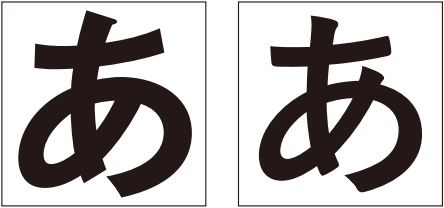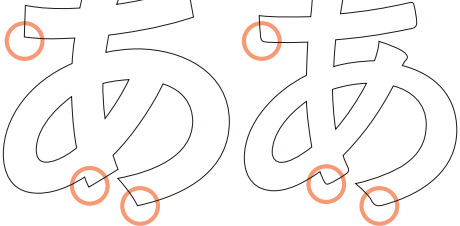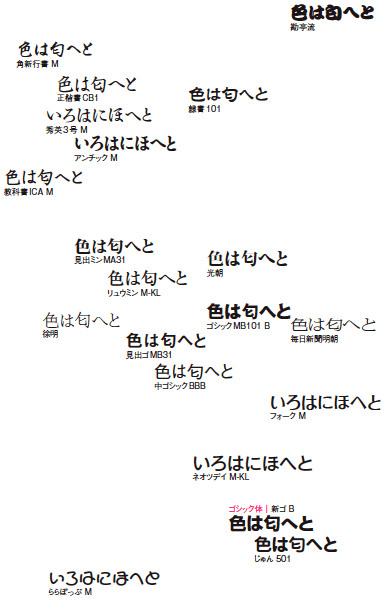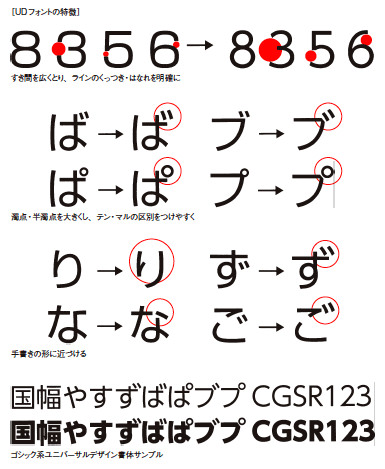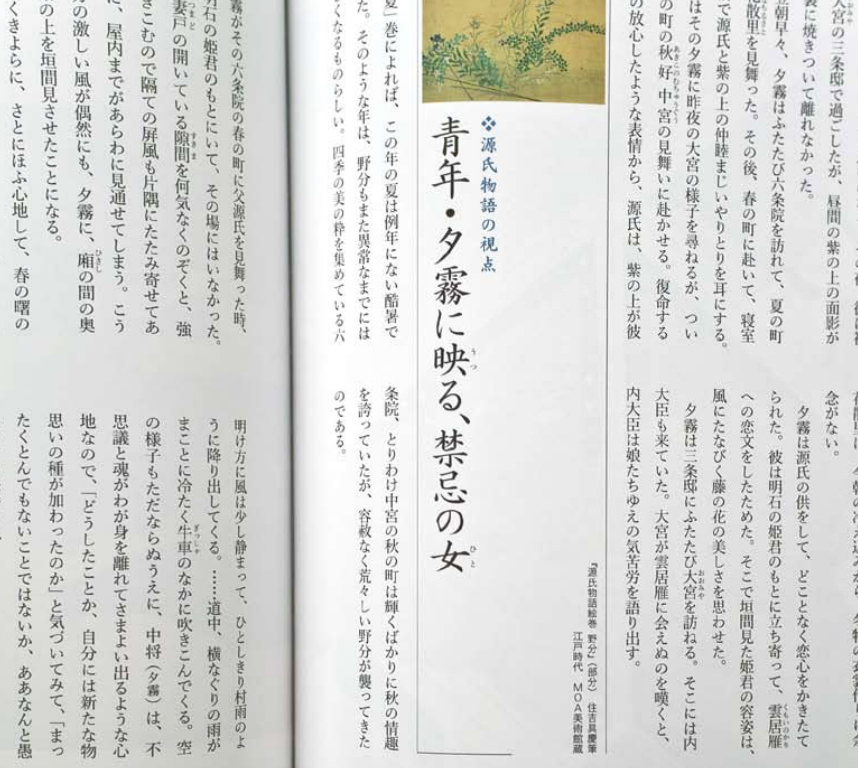
第九回 書 体 を 選 ぶ 2 和 文 書 体 を 見 分 け る
さて、前章では欧文書体の分類についてひととおり書いてみましたが、残念ながら、和文書体は未だに体系的に分類されるに至ってはいません。しかし、いくつかの試みを見ることはできます。なかでも、七章で紹介した、小宮山博史氏の「日本語書体の分類」(『基本日本語活字見本集成』収録)は、ひとつの基準になるものでしょう。それを承知の上で、ここでは、欧文書体に倣って、時代・かたち・用途で分類することを試みてみたいと思います。
時代に
よる分類
まず時代の分類を考えると、近代活字期、写真植字期、デジタル書体期の三期に分けることができます。
近代活字は、まだ和様が残る崩れた魅力の味わえる書体群を前期、築地体や秀英体といったおなじみの明朝体がかたちを成してくる後期の、二期に分けるのがいいでしょう。
近代活字の中心となる築地体は、改刻を重ね、多くのフォロワーを育てました。
それは、現代のかな書体や復刻書体にまで連なっています。おもな改刻書体として、写植期の石井明朝体(写研)、デジタル書体のリュウミンオールドかな(モリサワ)、游明朝体5号かな、36ポかな(字游工房)、復刻書体として、築地体初号仮名、後期五号仮名(大日本スクリーン)などを挙げることができます。秀英体も築地体を下敷きにして生まれた書体ですが、独自の発展を遂げて、今では、活字・写植・デジタル書体、三世代にまたがって開発が続けられている唯一の書体となりました。
築地体と秀英体は明朝体の二大源流といわれています。それぞれに特徴がありますから、これらを見分けるのはさほど難しくはないでしょう。同様の書風を持つゴシック体も近代活字期の書体に分類することができます。
写植期は、タイプフェイスデザインの開花期でもあり、さまざまな書体が登場します。なかでもフトコロが広くボディいっぱいに設計された書体がこの時期の特徴でしょう。仮名が大きくなるのもこのころです。ファミリー化され、見出しと本文が同じかたちになったことも特徴にあげていいでしょう。代表的な書体として、ナール、ゴナ、本蘭明朝(写研)、新ゴ、ツデイ(モリサワ)などを挙げることができます。デジタル書体ではありますが、ヒラギノ(大日本スクリーン)もこのグループの特徴を備えています。
デジタル書体は写植資産の電子化がようやく一段落したところですが、デジタル書体ならではの特徴も見えはじめています。たとえば、CTPなど印刷技術のデジタル化によってデータが精細に再現されるようになると、逆にシャープなエッジが嫌われるようになり、起筆部、終筆部だけでなく"はね"や"はらい"の先端も丸く処理されるようになりました。そういうエッジの丸めが特徴のひとつとなっています。
また、改刻書体の流行とも関連していると思われますが、写植書体とは逆に、小振りの文字が歓迎されるようになります。フトコロは絞られ、筆の運びを再現するようなかたちが好まれるようになってきました。そういった活字がえりが見受けられるなか、印刷・スクリーン表示兼用のアウトラインフォントやUDフォントへの取り組みにデジタル書体独自の発展を見ることができます。
三つの時代の特徴から分類すると、大きく、築地体、秀英体に代表される「オールドスタイル」、小塚明朝、新ゴといった「モダンスタイル」に分かれ、その中間の特徴を持つ、ヒラギノ明朝、ゴシックMB101といった「ミディアムスタイル」とでも呼べる三つに分けられるように思います。時代順と様式の変化が一致しないので欧文のように「トランジッショナル(過渡期の)」とは呼べないのが興味深いところです。
上段:築地体のフォロワー書体(改刻、復刻含む)。
左から石井中明朝体、リュウミン・オールドかな、游築五号仮名築地体後期五号仮名、游築36ポ仮名、築地体初号かな
下段:秀英体の改刻書体
左から秀英3号、秀英5号、秀英明朝体
左:MB101 DB 右:游ゴシック B
写植書体とデジタル書体の比較。デジタル書体としてつくられた游ゴシックの方が小振り
:MB101 DB 右:游ゴシック B
尖った角と丸められた角
時代による分類
かたちに
よる分類
欧文の場合はセリフによってかたちを規定していましたが、和文にはそういうこだわりのエレメントはありません。明朝体のウロコにも規範となるような強さは見受けられません。あえて何か基準を探すなら「筆づかい」だろうと考えています。運筆や筆勢がしっかり残っているかどうか、または、それをどの程度(どのように)抽象化しているのか、そういったことがかたちを分類する上で有効な基準になるように思います。明朝体の仮名が漢字と違う楷書のような特徴を持っているように、また、漫画書体の仮名がアンチック体であるように、筆書系の書体は思っている以上に使われています。そういった観点から今あるデジタル書体を分類してみたものが左ページのマップです。
並べてみると、筆の痕跡とかたちの相関など、これまで考えてこなかったことに改めて気づかされます。やはり分類の基準をひとつに定めることは、体系的に理解する上で重要なことなのでしょう。
[モリサワ書体におけるかたち(筆づかい)による分類マップ]
上下は筆の痕跡、左右はかたちの抽象度で分布した。左ほど手書きのかたちが残っている。距離は等歩度であることを心がけたが、うまくいっているのかどうかわからない。あくまで試案としてご勘弁いただきたい。
用途に
よる分類
UDフォントの特徴
最後に用途による分類です。和文活字は見出し用、本文用でタイプフェイスのデザインが異なります。先述の通りファミリー化によって区別がなくなったようにも思えますが、やはり、このふたつは分けて考えていいでしょう。同様に、書籍用と雑誌・パンフレット用も分けて考えることができます。
あとは、欧文と同じディスプレイ書体、デコラティブ(装飾)書体という分類。欧文と違うのは、用途別の専用書体が少ないこと。新聞書体と教科書体ぐらいでしょうか。これは、文字数の多さに起因するものと思われます。
前述のスクリーン表示兼用書体は、容量が軽いことに最大の特徴があり、そのため、文字数の制限はもとより、これまで成されてきた視覚調整すら省いている書体も見受けられます。しかし、本文程度のサイズではそれで見苦しいわけではなく、視覚調整の常識を疑った方がいいと思えるぐらいです。
UDフォントとはユニバーサルデザインのための文字のことです。バリアフリーであることを第一義とし、視力に障害や衰えがある人にも見誤りのないように、開口部をアキを広げたり、濁点、半濁点を大きくするなどの工夫が施されています。また、文字を直観的に見やすいように、手書きのかたちに近づけるようにかたちを変えてもいます。
いくつかあるUDフォントに共通の特色がどれくらいあるのか、そしてそれがどれほど有効であるのかは今後の検証を待たねばならないのですが、用途による分類のひとつに数えても問題ないでしょう。
近代活字以降の和文書体は、まだ歴史が浅いせいもあって、これまで積極的に整理・分類されることはありませんでした。文字数もさることながら、漢字、2種類の仮名、ラテンアルファベット、ローマ数字、アラビア数字と、さまざまな文字を組み合わせて使う日本語の文字表現の特性を考えると、体系的に把握することの困難さもあると思われます。逆に文字に対する自由度が損なわれるという考えもあるかも知れません。しかし、印刷書体が2000種を超え、これからオンスクリーンの表示書体と地続きになろうというところで、なんらかの書体の見分け方を手に入れなければ、書体選択もおぼつかなくなるような気がします。私は、欧文書体は「知ること」、和文書体は「考えること」で、書体選択の指標が手 にはいると考えています。
インタ
フェース
としての
書体選択
ここまで、書体選択ありきで話を進めてきましたが、ではなぜ書体を変えて文字を組まなくてはならないのでしょうか。
まず、分類の項で示したように、ある用途によってそれにふさわしい文字を選ぶということがあるでしょう。遠くから見る必要があるサイン書体は見やすいように、手元で長文を読むための文字は読みやすいように、文字の特徴を鑑みて選択します。あるいは、楽しく感じてもらうため、知的に見せたいなど、感情に訴えることも機能のうちでしょう。
機能面からだけではなく、美的な判断で書体を選ぶこともあります。太い文字の方がはっきりして見やすいことはわかっていても、もう少し細い方がきれいだ、などと言って細めの書体を選んだりします。
シニア用の読み物は大きな文字で組みます。視力の衰えへの配慮であれば、太めのゴシック体で組むのが一番読みやすいはずです。しかし、高齢者ほどゴシック体より明朝体を好むものです。理屈で考えれば、いくらウロコが付いているとはいえ、細い横画が見やすいはずもありません。しかし心理的には明朝体の方が読みやすく感じるようです。この場合、慣れや美意識が実際の機能を超えた例だと考えられます。
書体にはさらに内容を指し示す役割があります。たとえば、本文は細明朝体、見出しは太ゴシック、キャプションは中ゴシックで組むとします。そこに、脚註が加わればどうでしょう。本文と同じ細明朝でキャプションと同じ文字サイズで組まれていると、本文ともキャプションとも区別でき、本文に付随する内容であることを示すこともできます。
欧文では、文中の書名や作品名をイタリック体で表記します。和文では重要な語句をボールドにして、それがキーワードであることを知らせます。こういったことは一種の文法ですから、読み手の能力が必要になります。
考えてみれば、タイポグラフィは文章のインタフェースをつくっており、書体選択はそのための重要な役割を担っているのです。
見出し、本文、解説、2 種類のキャプションが書体やサイズ、組み方向によって示されている
『別冊太陽王朝の雅源氏物語の世界』(平凡社)
デザイン:永原康史事務所
ラピッド
コミュニ
ケーション考
言うまでもなく、文字は文を綴ります。文字を組むとは文字を並べてことばにすることです。それを重ねていけば文章になります。では、ことばや文章のためだけに書体を選ぶのでしょうか。そのために何万という書体が必要かといえば、答えは否でしょう。
デザインは表層をつくります。内容(コンテンツ)をつくるわけではありません。したがって、デザインとコンテンツは分けて考えることができます。では、意味は内容にだけあって表層にはないのでしょうか。そんなことはありません。表層、つまり表面に見えて現れているところだけでも伝わることがあります。
ファッションがいい例でしょう。豊かになった今はあまり見られないかも知れませんが、かつて若者はファッションで自分の所属を表明していました。ヤンキー独特の髪型や服装が良い例です。そういう特殊なファッションでなくとも、ホワイトカラー、ブルーカラーなどという呼び方も外見から来ています(白いワイシャツとブルーデニムの作業衣から、事務職と作業労働者のことを指します)。
文字は読む前に見ます。見る前に読むことはあり得ない。必ず、読む前に見ます。そして、その見た瞬間に伝わるものがあります。表層の情報をインプットしてから内容を読むのです。したがって、選ばれた書体や施された組み方は、内容に影響を与えます。
たとえば、友人から結婚式の案内が来たとします。封筒を開けて文面が楷書で書かれていればフォーマルな披露宴への招待状でしょう。ゴシック体ならカジュアルな友人主催の二次会です。それは、内容を読む前に伝わります。
漢字の多い黒々とした版面は難しい文章のように感じます。逆に、かなが多く明るいページは取っつきやすいものです。版面の濃度は文字のウエイト(太細)で調整することができます。書体の選択ひとつで、読書への心構えをつくることもできるのです。
書体にはその背景に歴史や役割があります。かたちから来る印象があります。
たしかに、それらを読み取る能力を持っている人はごく一部に限られます。しかし、多用な書体に触れる機会が多い現代において、日常のうちに書体が持つニュアンスを理解している人が増えているのも事実です。文字を見た瞬間のコミュニケーション(ラピッドコミュニケーション)をデザインすることの重要性は高まっていると言えるでしょう。
文字は読む前に見る。タイポグラフィは内容への誘いであると同時に、批評であり、意見でもあるのです。